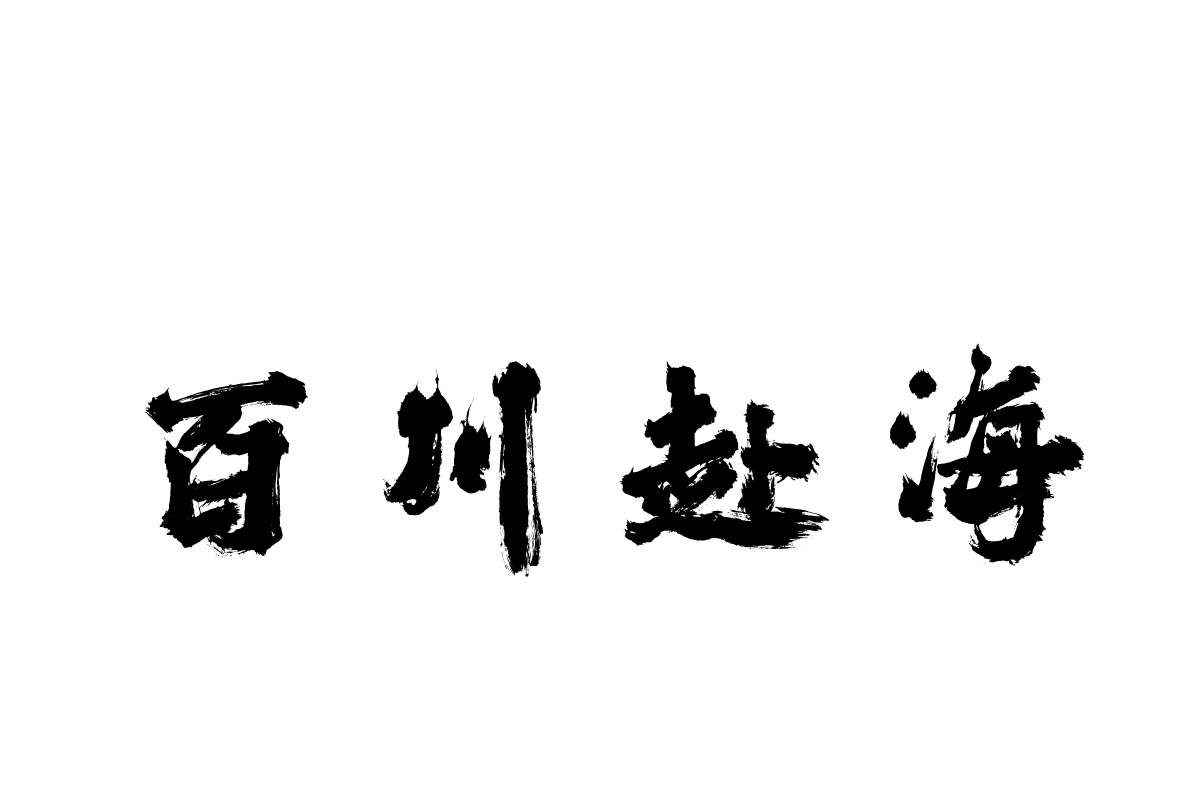
汉仪黄科榜书是一款由当代青年书法家、汉仪字库签约书写人黄科创作的书法艺术字体,具有以下特点:
1. **视觉冲击力**:
– 这款字体的视觉冲击力极强,形式美感与设计感十足。
– 突破了传统书写时的条条框框束缚,大胆地融合了各种现代与商业元素。
2. **大字特点**:
– 一个字一张纸,一共书写了九千余张,体现了其“大”的特点。
– 字库大,尽量保留了书写时丰富的笔触细节,实现了最大程度的细节还原。
3. **创新风格**:
– 从传统中来又能区别于传统书法,更具现代感。
– 呈现了一派全新的气象,与现代设计元素结合得天衣无缝。
4. **丰富字符**:
– 繁体和简体各有8254个字符和7508个字符,字符分布范围广泛。
– 包括基本拉丁文、拉丁文扩充系列、国际音标扩展等字符类型。
综上所述,汉仪黄科榜书以其独特的大字特点、创新风格以及丰富的字符类型,成为了一款具有视觉冲击力和现代感的书法艺术字体。它不仅在视觉上给人留下深刻印象,而且在实用性上也能满足不同场景的需求。